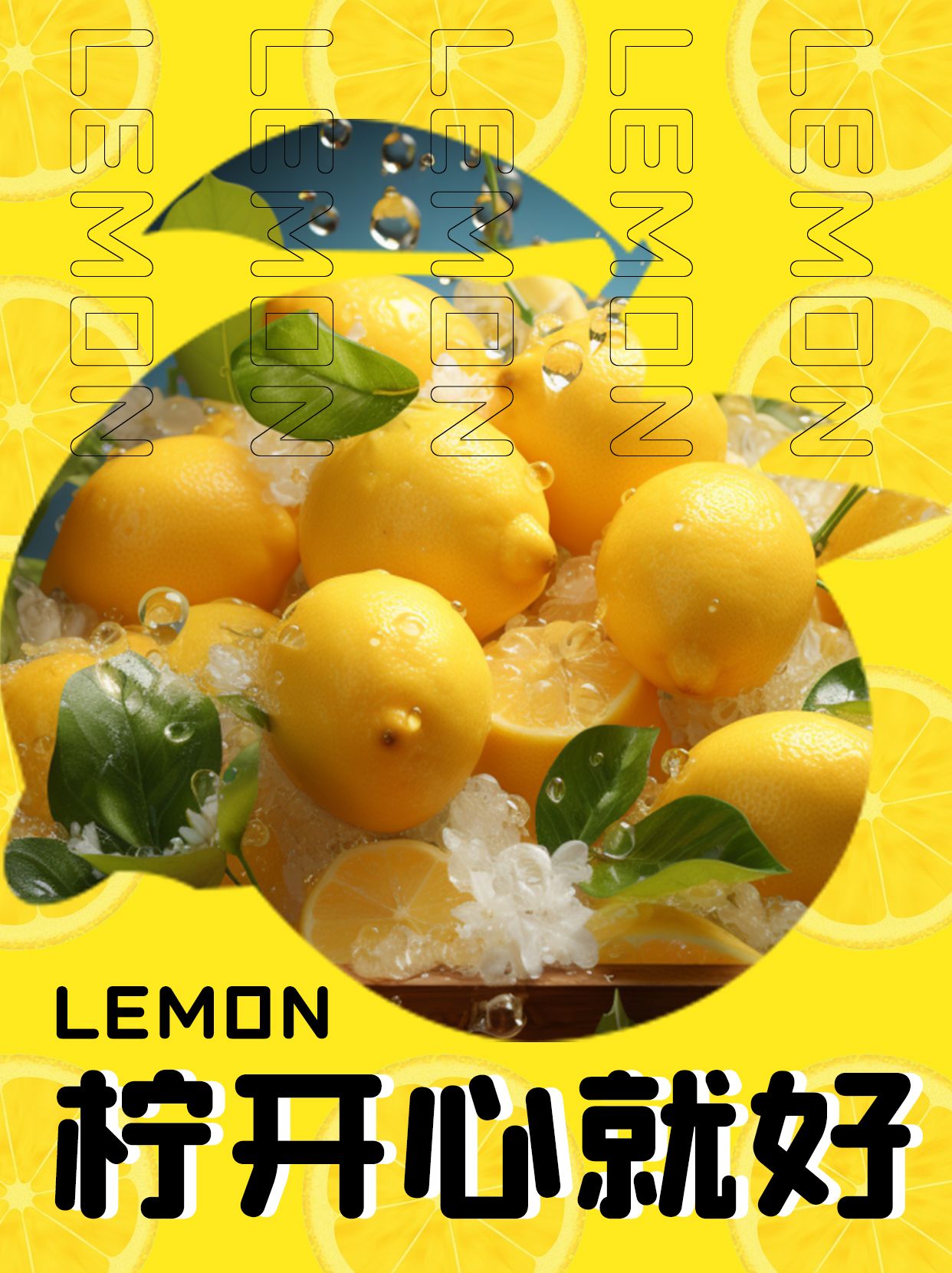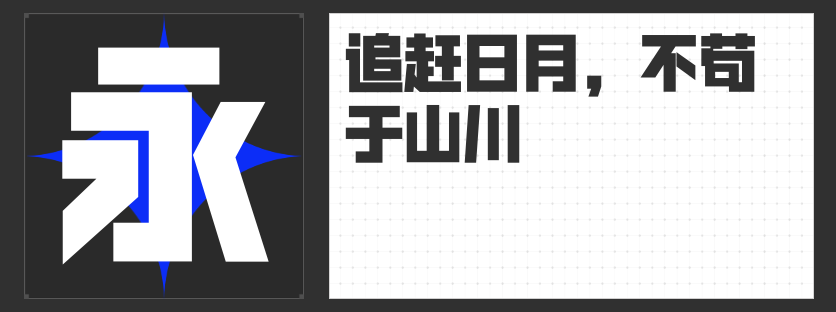
标题字体推荐:为设计注入灵魂的魅力之选
在设计的世界里,标题字体犹如画龙点睛之笔,能瞬间抓住观众的注意力,传递核心信息。今天,就为大家推荐四款独具魅力的标题字体,助力你的设计脱颖而出。
一、励字开拓者简 超黑
励字开拓者简 超黑,字型方正,中宫较大,重心适中,给人一种沉稳大气之感。全部采用直线笔画,横平竖直,棱角分明,简约而不失力量感。起笔和收笔以平切为主,内部几何处理空间均匀,整体平衡感极佳。部分钩笔画去钩处理,撇、捺、点竖直化,带来强烈的镜像视觉效果,新颖独特。而且它还包含众多网红流行用字,无论是时尚潮流的设计,还是科技感十足的作品,都能轻松适配。
二、励字志向黑简 特粗
励字志向黑简 特粗,巧妙地将圆体与黑体融合。在笔画拐角增加适当的外圆角,在整体稳重大气的字形中增添了一丝灵动。字面充实,结构稳定,特别适配屏显使用。它既有黑体的刚劲有力,又有圆体的柔和亲切,适合用于各类宣传海报、活动标题等,能在传递信息的同时,给人留下深刻的印象。
三、励字铁拳简 超级黑
励字铁拳简 超级黑,是一款极具创意的黑体字。笔画粗壮、字面宽大,饱满的块面感以及折角圆设计,带来强烈的视觉冲击,犹如铁拳出击,横扫千军。在需要突出重点、展现强大气场的标题设计中,它无疑是绝佳之选,能瞬间提升作品的视觉张力。
四、励字圆梦简 大黑
励字圆梦简 大黑,字型圆润柔和,笔画为直线笔画,以竖折笔画代替部分弧线,简洁明了。笔画起笔、收笔和转折处融合圆体自然的圆弧风格,中宫松散,外圆内方,既有圆体的亲和力,又有黑体的稳重感。它适合用于温馨、励志类的设计标题,能传递出温暖而坚定的力量。
这四款标题字体各具特色,无论是简约时尚、灵动活泼,还是霸气十足、温暖亲切,都能满足不同设计需求,为你的作品增添独特的魅力。